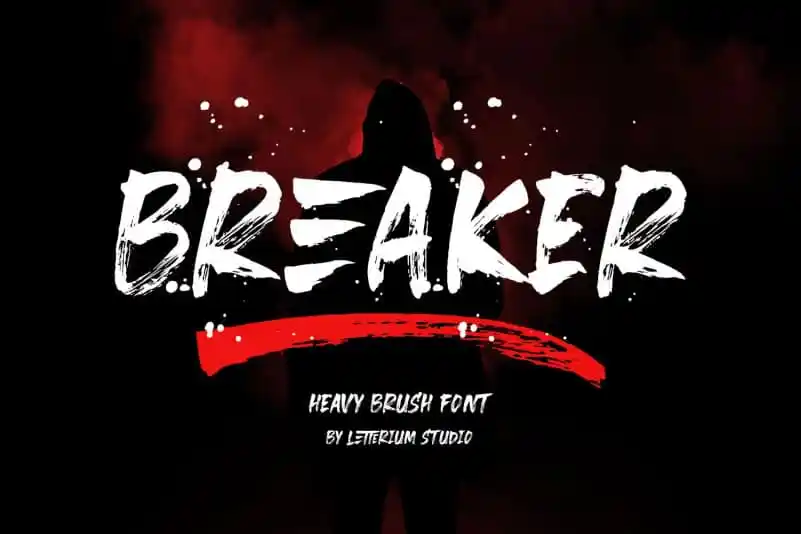
Breaker Brush Font – Fonte Grátis
Breaker Brush Font
A Breaker Brush Font é uma nova escolha para quem busca um tipo heavy brush que transmite emoção sem precisar escrever muito. Criada pela Letterium Studio e desenvolvida especialmente com letras maiúsculas, ela carrega uma atmosfera sinistra pronta para o design de posters, t-shirts, mochilas, bolsas, xícaras, selos, subtítulos, logotipos, cartões de convite e muito mais. Com seu estilo gráfico e sua capacidade única de dominar diferentes formatos de texto e imagens, a Breaker Brush Font é ideal para quem deseja dar um toque criativo em qualquer projeto, sejam eles materiais publicitários ou design de produto. Através do uso desta fonte, você pode capturar o olhar de quem vê e tornar sua marca inesquecível. Experimente ela hoje e encontre a perfeita para seus projetos visuais!